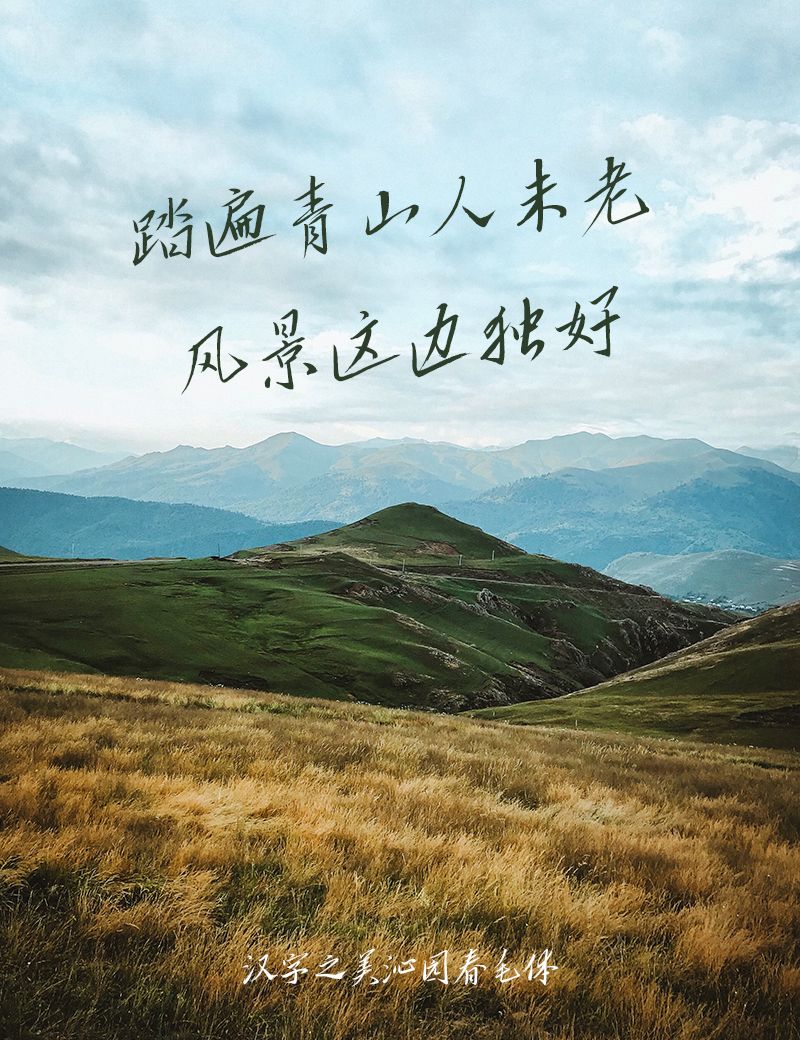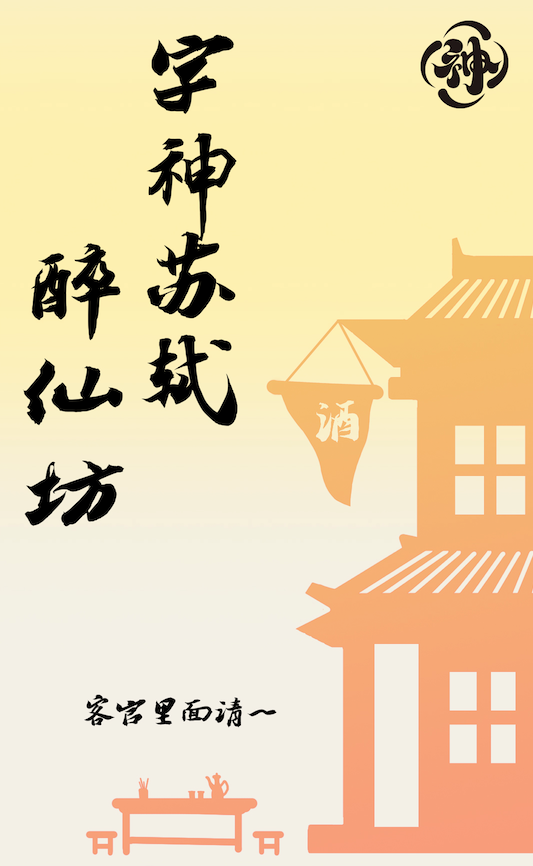
🌸妇女节精神,字里行间尽显巾帼风采!推荐三款绝美字体💖
在这个属于所有女性的特别日子里,我们不仅庆祝女性的力量与智慧,也致敬那些能在字里行间传递出独特女性魅力的字体。今天,就为大家推荐三款能够完美诠释妇女节精神的字体产品,让你在书写与设计中,展现那份独特的柔美与坚韧!
1️⃣ 龙书道陈忠建文青体 🌿
这款字体融合了传统书法与现代审美,既有龙书道的雄浑大气,又不失文青特有的清新雅致。用它来书写妇女节祝福语,既能表达对女性的崇高敬意,又能传递出温暖人心的细腻情感。每一个字都仿佛在诉说着女性的温柔与力量,让人一眼难忘。
2️⃣ 汉字之美沁园春毛体 🌸
提到女性,怎能不提那份由内而外的柔美与坚韧?汉字之美沁园春毛体,以其独特的笔触和流畅的线条,完美展现了女性的柔美与力量。这种字体既有毛泽东书法的豪放不羁,又不失女性特有的细腻温婉。用它来创作妇女节主题的海报或文案,定能让人眼前一亮,感受到那份独特的女性韵味。
3️⃣ 字神苏轼豪放体  🔥
谁说女性不能豪放?苏轼的诗词中,那份不羁与洒脱,正是许多现代女性所追求的精神境界。字神苏轼豪放体,以其独特的书法风格和豪迈的气息,让人仿佛看到了那些勇敢追求梦想、不畏挑战的女性形象。用它来书写妇女节励志语,定能激励更多女性勇往直前,绽放属于自己的光彩!
三款字体,三种风格,却能共同诠释出妇女节的精神内涵。在这个特别的日子里,让我们一起用文字传递爱与力量,向所有女性致敬!💪💖